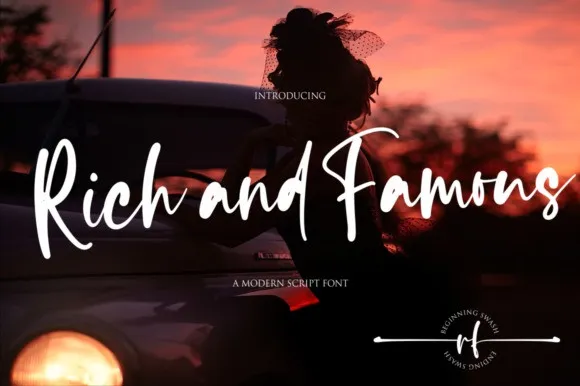
Rich and Famous Font – Download Grátis
Esta é uma fonte script escrita a mão com um fluxo natural. Foi projetada pela NJStudio especialmente para aquelas pessoas que precisam de um visual belo e renovador em suas criações. Esta font, PUA encodada, significa que você pode acessar facilmente todos os gráficos e swashes. A fonte ‘Rich and Famous Font’ é uma opção perfeita para designers que desejam trazer uma sensação de naturalidade à sua arte digital, transformando o seu trabalho em algo atraente e profissional. Esta font destaca-se pelo seu design elegante e pelo seu fluxo fluido, tornando-a um atalho rápido e divertido para aqueles que procuram uma nova abordagem para suas criações de escrita.